Примеры шрифты: Лучшие 20 рукописных и каллиграфических шрифтов для презентации
Коллекция MegaFont NOW впечатляет объемом и разнообразием. Она включает в себя 7500 наиболее красивых шрифтов от SoftMaker, среди которых многие известные классические шрифты разных времен и эпох.
В MegaFont NOW вы найдете отличный шрифт на любой случай. Коллекция шрифтов отличается огромным разнообразием стилей, которые можно использовать для любых целей: классические и современные текстовые шрифты, элегантные каллиграфические шрифты, броские шрифты для заголовков и необычные декоративные шрифты.
Во всех шрифтах представлен полный набор символов
со всеми диакритическими символами и умлаутами западноевропейских языков. Многие шрифты также включают в себя центральноевропейские и турецкие символы. Все шрифты содержат знак евро с индивидуальным дизайном и оптимизированы для красивого качественного отображения на экране и на бумаге.
Многие шрифты в пакете MegaFont NOW поддерживают расширенные типографские возможности OpenType для создания эстетической типографики с помощью графического программного обеспечения, такого как Adobe Creative Suite, например посредством использования альтернативных букв, автоматических лигатур и символов старинного стиля.
Паратайп | Классификация шрифтов
Акцидентные
К этой группе относятся шрифты, не укладывающиеся в предыдущие группы классификации, а также специально предназначенные для акцидентного набора и имитирующие определенный исторический стиль или декоративную обработку формы, например, Модерн, Ар Деко, оп-арт, контурные, выворотные, трехмерные, фактурные, орнаментальные, трафаретные, машинописные, экранные, с рваным контуром и т.
Экстремальные
Акцидентные шрифты, сохраняющие привычный рисунок и укладывающиеся в рамки классификации, принятой для текстовых шрифтов. Шрифты для очень крупных кеглей, крайние варианты шрифтов привычного рисунка.
- ITC FatFace
Экстремальные шрифты делятся на:
-
Сверхжирные
-
Сверхтонкие
-
Сверхширокие
-
Сверхузкие
-
Сверхконтрастные
Геометрические
Собранные из простых геометрических форм и лишь условно напоминающие знаки традиционной формы.
Экспериментальные
Акцидентные шрифты, резко отличающиеся по форме знаков, шрифты с измененным контуром знаков, измененной формой знаков, гибридные, «живые» шрифты и др.
Нарушения контура
Акцидентные шрифты или начертания с измененным контуром знаков (грубым, рваным, имитирующим оттиск на шероховатой бумаге и т.
- Academy Rough
- AdverGothic Rough
- Bernhard Rough
- Compakt Rough
- Compakt Wind
- Courier Rough
- Crash
- Guenter
- Hermes Rough
- Mistica
- Nazhdak
- Ottisk
- Wind
Нарушения формы
Акцидентные шрифты, резко отличающиеся по форме знаков, с измененной формой знаков или их деталей, гибридные – составленные из знаков разных гарнитур или имеющие знаки, склеенные из нескольких частей от разных гарнитур, и т.д.
- Bistro
- Compakt Broken
- Compakt Dance
- Cracker
- Dead History Cyrillic
- Dikovina
- Drunk
- Duetto
- FaRer
- Garbage
- Garbedge
- Graffiti
- Gulitov
- HotSauce
- KvadratZ
- MonoCondensed Zoom
- Monte Summa
- Musor
- Pollock
- Probbarius
- Quartet Cyrillic
- Shaltai
- Somaton
- Strelochnik
Имитации
Основанные на реально существующем или существовавшем способе построения и/или воспроизведения знаков.
Деревянные литеры
Машинописные
Акцидентные и текстовые шрифты, по форме имитирующие шрифт пишущей машинки, а также любые шрифты с одинаковыми ширинами знаков. Моноширинные шрифты применяются для набора таблиц и технических текстов, а машинописные для имитации машинописного текста и для акциденции.
1 / 100- Courier
- Courier (APC)
- Courier Monotonic Greek
- Courier Polytonic Greek
- Jatran
- MonoCondensed
- Optimus
- Priamoj
- Secretary
- Telegraph
Электронные
Акцидентные шрифты, эксплуатирующие эстетику компьютерных, экранных и других близких по назначению шрифтов.
Шрифты OCR
Акцидентные шрифты, имитирующие форму знаков шрифтов для машинного оптического распознавания, штриховых кодов и т.д.
- Countdown
- OCR One
- Techno28
Экранные
Акцидентные шрифты, имитирующие форму и фактуру знаков экранных шрифтов низкого разрешения.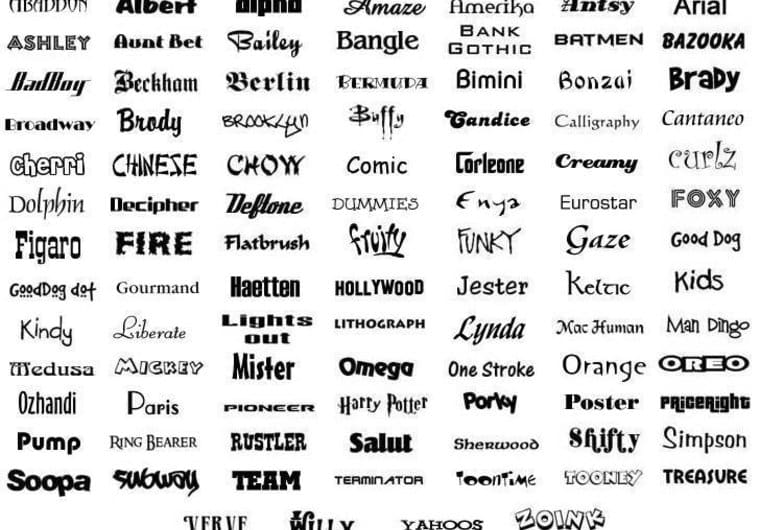
- Dotage
- Ecyr
- FixSys
- Lo-Res Nine Cyrillic
- Mobul
- Multicross
- AZ Poligon
- Strob
- Tablo
Шрифты табло
Акцидентные шрифты, имитирующие форму и фактуру знаков разнообразных шрифтов для информационных табло, матричных принтеров, жидкокристаллических дисплеев и других устройств, воспроизводящих шрифт с низким разрешением.
- Crystal
- Electronica
- Perfo
- Performance
Трафаретные
Акцидентные шрифты, имитирующие надписи, выполненные по трафарету. Знаки состоят из отдельных элементов, разделенных белыми перемычками. Иногда элементы знаков заполнены различными фактурами.
- Aksent
- Bardi
- Cliche
- Debby
- DJ Parade
- FavoritTraf
- Futura Eugenia
- Glasten
- Mania
- Nelma
- Plain
- Start
- Trafaret
- New Zelek
Натурные
Декорированные
Сюда относятся декоративные шрифты, предназначенные для акциденции, не укладывающиеся в предыдущие группы классификации, форма которых имеет преувеличенные детали или подверглась изменению с целью усиления декоративности.
Орнаментированные
- Orbi
Текстурированные
- Wind
Контурные, трехмерные, фактурные и выворотные
Акцидентные шрифты, знаки которых образованы контурами различной толщины, иногда с заполнением внутри, оттенением или и тем и другим. Иногда штрихи таких шрифтов заполнены фактурами или представляют собой негативное изображение.
- AdverGothic Cameo Bold
- Borjomi Decor
- Dotage
- Dynar Shadow
- EdgeLine Shadow
- Europe Shadow
- Futura Futuris Shadow
- Futura Futuris Volume
- Inform Shadow
- Izhitsa Shadow
- Josephine
- Leshy
- Sans Decor
- Tauern
- Template Gothic Cyrillic
Типы шрифтов, примеры и когда их использовать
Независимо от характера вашего дизайнерского проекта, различные типы шрифтов и окончательный выбор шрифта имеют решающее значение.
Шрифты помогают передать сообщение и передать чувство, связанное с сообщением. Выбор правильных шрифтов для ваших логотипов и других элементов дизайна может помочь в восприятии вашего сообщения или фирменного стиля.
какие существуют типы шрифтов?
Существует множество различных типов шрифтов, но в целом их можно разделить на следующие широкие категории:
- Шрифты с засечками: Эти шрифты имеют маленькие линии или «засечки» на концах толстых и тонких штрихов каждой буквы. Шрифты с засечками (например, New Roman) часто используются для печатных материалов, таких как книги и газеты, поскольку считается, что их легче читать в больших блоках текста.
- Шрифты без засечек: Шрифты без засечек не имеют засечек и имеют чистый современный вид. Они часто используются в качестве веб-шрифтов; в цифровых медиа, таких как веб-сайты и мобильные приложения, поскольку их легче читать на экранах.
- Шрифты Script: Шрифты Script имитируют рукописный почерк и имеют плавный элегантный вид.
Они часто используются для официальных приглашений и объявлений. - Дисплейные шрифты: Дисплейные шрифты предназначены для привлечения внимания и часто используются для заголовков и заголовков. Они бывают разных стилей, от смелых и массивных до изящных и богато украшенных.
- Моноширинные шрифты: Моноширинные шрифты имеют фиксированную ширину, что означает, что каждый символ занимает одинаковое количество места. Они часто используются для программирования кода и других технических приложений, где важно выравнивание.
- Рукописные шрифты: Рукописные шрифты имитируют рукописный текст и напоминают рукописную каллиграфию, чтобы добавить индивидуальности дизайну или логотипу бренда. Эти шрифты и каллиграфические шрифты часто используются для приглашений и других неформальных сообщений.
- Декоративные шрифты: Декоративные шрифты очень стилизованы и используются в особых случаях или для придания дизайну визуального интереса.
Декоративные шрифты бывают разных стилей, от богато украшенной каллиграфии до причудливых мультяшных шрифтов.
Как выбрать свой шрифт в мире с миллионами различных типов шрифтов
В наши дни у нас есть больше вариантов и различных переменных классификации шрифтов, чем когда-либо прежде.
Доступны тысячи шрифтов в различных стилях.
Однако навигация по различным шрифтам и выбор лучших шрифтов могут быть сложными.
В этом руководстве мы познакомим вас с основными типами шрифтов (от популярных шрифтов без засечек до декоративных), с тем, как они используются и как выбрать правильный шрифт, который передает нужную вам атмосферу.
Содержание
- Пять типов шрифтов
- Как выбрать шрифт?
Используйте красивые привлекательные шрифты в визуальных материалах и дизайне с помощью Piktochart. Попробуйте бесплатно.
Пять типов шрифтов
Несмотря на множество вариантов шрифтов, здесь мы перечисляем пять основных типов шрифтов, указатели, когда их использовать, и несколько примеров.
1. Шрифты с засечками
Примеры шрифтов без засечек : Georgia, Times New Roman, Beirut, Mermaid, Bodoni, Roslindale
Источник изображения: Donauhof WienШрифты с засечками относятся к числу оригинальных классических гарнитур, обычно используемых для профессионального и сложного дизайна.
Засечки включают небольшие выступы, завершающие штрихи их форм букв (называемые засечками, откуда этот стиль и получил свое название). Появившись в 1500-х годах, первые засечки были засечками в старом стиле. Этот стиль включает Garamond и Goudy Old Style. Преемники засечек старого стиля назывались переходными засечками, которые впервые появились в 1700-х годах. Эти шрифты имели высокий контраст штрихов и были более вертикальными, чем их предшественники в старом стиле.
Вы можете отличить шрифт с засечками от других по крошечным черточкам в верхнем и нижнем штрихах каждой буквы.
Что делает шрифты с засечками уникальными?
Шрифты с засечками уникальны, поскольку они имеют небольшие линии или завитушки, известные как «засечки», на концах штрихов, составляющих каждую букву.
Эти засечки придают шрифту более традиционный классический вид, который часто ассоциируется с печатными изданиями, такими как книги, газеты и журналы. Шрифты с засечками предназначены для удобного чтения в больших блоках текста, что делает их популярным выбором для объемного контента, такого как романы или академические статьи. Эксперты-типографы утверждают, что это самые разборчивые и легко читаемые шрифты без засечек.
Засечки в шрифтах с засечками помогают направлять взгляд читателя вдоль строки текста, облегчая его отслеживание и снижая нагрузку на глаза. Это связано с тем, что засечки создают «базовую линию» для каждой строки текста, что помогает глазу быстро и легко выровнять текст. Шрифты с засечками часто описываются как имеющие более формальный или традиционный вид и обычно используются в контекстах, где дизайнер хочет передать ощущение элегантности, изысканности или авторитетности.
Источник изображения: Галерея Drella В результате они являются первыми шрифтами, которые приходят на ум для различных проектов, таких как логотипы, печатные копии и веб-сайты.
И они придают вашему дизайну старомодный элегантный оттенок.
Шрифт с засечками считается заслуживающим доверия, консервативным и безопасным выбором практически в любом контексте, например:
- Заголовки и подзаголовки
- Основной текст, будь то короткие или длинные страницы текста
- Большие или маленькие размеры
Однако, как правило, их не рекомендуется использовать, если вам нужны крошечные размеры шрифта. Если вы разрабатываете что-то в основном для цифровых экранов, вы можете рассмотреть другие типы шрифтов, которые мы обсудим ниже.
2. Шрифты без засечек
Примеры: League Spartan, Fredoka One, Aileron, Bebas Neue, Zelda
Источник изображения: Blog With Joy по умолчанию на цифровых устройствах.Вы можете найти их почти в каждой книге, документе или другой публикации.
Шрифт без засечек относится к шрифтам без штрихов, уникальным для шрифтов с засечками.
В чем разница между шрифтами с засечками и шрифтами без засечек?
Основное различие между шрифтами с засечками и шрифтами без засечек заключается в том, что шрифты с засечками имеют тонкие штрихи/небольшие линии или завитки на концах штрихов, составляющих каждую букву (известные как «засечки»), в то время как шрифты без засечек имеют нет.
Шрифты с засечками часто ассоциируются с печатными материалами, такими как книги, образовательные ресурсы, газеты и журналы, и предназначены для удобного чтения больших блоков текста. Засечки в шрифтах с засечками помогают направлять взгляд читателя вдоль строки текста, облегчая его отслеживание и снижая нагрузку на глаза. Шрифты с засечками часто описываются как имеющие более традиционный или классический вид и обычно используются в контекстах, где дизайнер хочет передать ощущение элегантности, изысканности или авторитетности.
С другой стороны, шрифты без засечек часто ассоциируются с цифровыми медиа, такими как веб-сайты, мобильные приложения и платформы социальных сетей. Они имеют чистый современный вид и часто используются для коротких фрагментов текста, таких как заголовки или подписи. Шрифты без засечек предназначены для удобного чтения на экранах, которые, как правило, имеют более низкое разрешение, чем печатные носители. Их часто описывают как более непринужденные или неформальные, с неоклассическим дизайном.
Они обычно используются, когда дизайнер хочет передать ощущение современности, простоты или дружелюбия.
В целом, выбор между шрифтами с засечками и без засечек зависит от конкретного контекста и целей дизайна. Шрифты с засечками часто используются для формального или традиционного контекста, а шрифты без засечек часто используются для неформального или современного контекста.
На протяжении всей истории они не были так популярны, как засечки, но стали заметны с появлением компьютеров и других цифровых устройств.
Это было примерно тогда, когда немецкие дизайнеры экспериментировали с формами букв без ножек и разработали культовые шрифты, которые чрезвычайно популярны сегодня, такие как Helvetica и Futura.
Шрифты без засечек также можно разделить на несколько подкатегорий, включая гротескные, квадратные, геометрические и гуманистические стили. Бренды, которые используют шрифты без засечек в своих логотипах: LinkedIn, Calvin Klein и The Guardian.
Разборчивый и жирный шрифт без засечек теперь является синонимом простоты, эффективности и современного внешнего вида.
Они также считаются самыми экономичными и чистыми шрифтами.
Из-за отсутствия мелких штрихов в буквах шрифты без засечек менее детализированы и более разборчивы в определенных контекстах.
Например, они хорошо адаптируются даже в небольших размерах или на цифровых экранах.
Они легко читаются независимо от размера шрифта или длины текста.
Это делает шрифт без засечек мастером на все руки.
Кроме того, шрифт без засечек считается жирным и более творческим шрифтом, чем традиционный и консервативный шрифт с засечками.
По этой причине они чаще используются в логотипах и заголовках, чем в длинных абзацах.
Выберите шрифт без засечек, если вам нужен минималистичный или современный вид.
3.
Шрифты ScriptПримеры шрифтов Script : Alex Brush, Broadley, Pacifico, Barista, Great Vibes
Источник изображения: Begindot Шрифты Script идентифицируются курсивом, рукописным или каллиграфическим стилем буквы.
Их формы букв и стили шрифта больше всего похожи на рукописный почерк.
Благодаря этому они сочетают изящность стилей шрифтов с засечками с более красивым и аутентичным дизайном.
Источник изображения: BegindotТип шрифта script лучше всего использовать для романтических обложек книг и свадебных приглашений или правильный шрифт, когда вы хотите, чтобы ваши дизайны выглядели более историческими.
И они исключительно хорошо работают в логотипах, заголовках и цитатах.
Сила этого типа шрифта заключается в его уникальности и смелости, но за счет удобочитаемости. Поэтому очень важно использовать его экономно.
Шрифты Script обычно не используются для длинных текстов или отрывков.
4.
Экранные шрифтыПримеры этого семейства шрифтов: Gilroy, Athetik, Made Canvas, Margaret, Playfair
Источник изображения: Neuron Themes Экранные шрифты (также известные как декоративные) самые сложные шрифты идентифицировать, поскольку они не следуют каким-либо общим правилам.
Эти шрифты являются одними из самых уникальных и охватывают множество стилей, таких как граффити, абстрактные и трехмерные формы.
Источник изображения: Neuron Themes5.
Шрифты Slab SerifПримеры : Typnic, Comply, Artegra, Bebop, Fanatix
Источник изображения: Design InspirationШрифты Slab serif самые заметные и самые громкие засечки. Думайте об этих шрифтах с засечками как о более энергичном и восторженном брате спокойных и классических шрифтов без засечек.
Шрифты с засечками возникли в начале 19 века, когда была разработана новая технология печати, называемая «плоскими» или «египетскими» шрифтами. Эти шрифты были разработаны, чтобы быть смелыми и привлекающими внимание, с толстыми прямоугольными засечками, которые создавали характерный «блочный» вид.
Первые шрифты с засечками были разработаны Винсентом Фиггинсом, известным типографом и шрифтовиком из Лондона, в начале 1800-х годов.
Фиггинс создал шрифт Antique с толстыми, похожими на плиты засечками и жирными штрихами. Шрифт имел мгновенный успех и быстро стал популярным в рекламе и дизайне плакатов.
В США первые шрифты с засечками были разработаны компанией American Type Founders в середине 19 века. Эти шрифты были основаны на более ранних британских образцах, но были адаптированы для американского рынка и стали особенно популярными в газетных заголовках и рекламе.
Они предназначены для чтения с большого расстояния и активно используются на рекламных щитах, брошюрах и плакатах в течение нескольких десятилетий.
Источник изображения: Design InspirationВ последнее время они также превратились в формы, которые можно использовать для длинных абзацев текста. Шрифт Clarendon – хороший пример.
В целом шрифты с засечками передают винтажную художественную атмосферу и неоспоримый суровый атлетизм. Они отлично подходят для брендов товаров для активного отдыха.
Как выбрать шрифт?
Мы рассмотрели несколько идеальных сценариев использования основных типов шрифтов.
Но есть некоторые дополнительные факторы, которые необходимо учитывать при выборе палитры шрифтов для вашего дизайн-проекта. Итак, давайте посмотрим на них.
1. Индивидуальность вашего бренда
Выбранные вами шрифты должны соответствовать визуальным атрибутам вашего бренда и его нише. Например, типографика косметического бренда будет отличаться от ИТ-бренда.
Отличный способ понять это — изучить шрифты, используемые брендами, похожими на ваш. Вам не нужно красть одни и те же шрифты, но вы получите общее представление о том, на что стрелять.
По словам Скотта Чоу из Blog Starter, индустрия моды является ярким примером этой тенденции, где более 70% модных брендов используют шрифты Geometric San Serif.
Также подумайте, какие цвета вы собираетесь использовать. Вы бы хотели использовать светлые цвета с экстравагантными шрифтами и насыщенные цвета с неброскими шрифтами.
Если, например, и цвета, и шрифты кричащие, то ваш дизайн будет больше похож на цирковую афишу.
2. Количество используемых шрифтов
Выберите один шрифт в качестве основного. Это будет использоваться чаще всего, особенно в больших размерах, таких как заголовки. Вы можете стать смелым и уникальным при выборе основного шрифта, потому что он нужен не только для удобочитаемости, но и для создания настроения.
После этого выберите другой шрифт в качестве вторичного. Это будет использоваться для основного текста и других больших абзацев. Поскольку удобочитаемость имеет важное значение, вы должны в первую очередь обращать внимание на то, чтобы шрифт был простым и легко читаемым.
При необходимости вы также можете выбрать третий шрифт. Вы можете использовать его экономно для таких элементов, как призыв к действию, кнопки, меню и т. д. Он может быть немного причудливым, как основной шрифт, но он не должен затмевать другие ваши шрифты.
Всегда помните об иерархии шрифтов при их использовании в проекте. Ваши основной, дополнительный и другие шрифты имеют разный вес и должны использоваться как таковые.
Бывают случаи, когда оправдано использование более трех шрифтов, но золотое правило в большинстве случаев — придерживаться только двух или трех.
3.
Контраст между шрифтамиСледующим важным аспектом является правило контрастов. Это вступает в игру, когда вы сочетаете два или более шрифта в качестве заголовка + подзаголовка или заголовка + основного текста.
Использование двух одинаковых шрифтов — прямой путь к катастрофе. Ваш дизайн будет выглядеть запутанным и непрофессиональным. Всегда выбирайте шрифты, которые кажутся очень разными при объединении.
Например, вы можете сопоставить рукописный шрифт в заголовке со шрифтом с засечками в основном тексте. Или соедините шрифты без засечек (например, Brandon Grotesque) с засечками (например, Baskerville).
Пример сочетания шрифтов с хорошей контрастностью Комбинируемые шрифты не обязательно должны принадлежать к разным семействам шрифтов, если они имеют достаточную контрастность.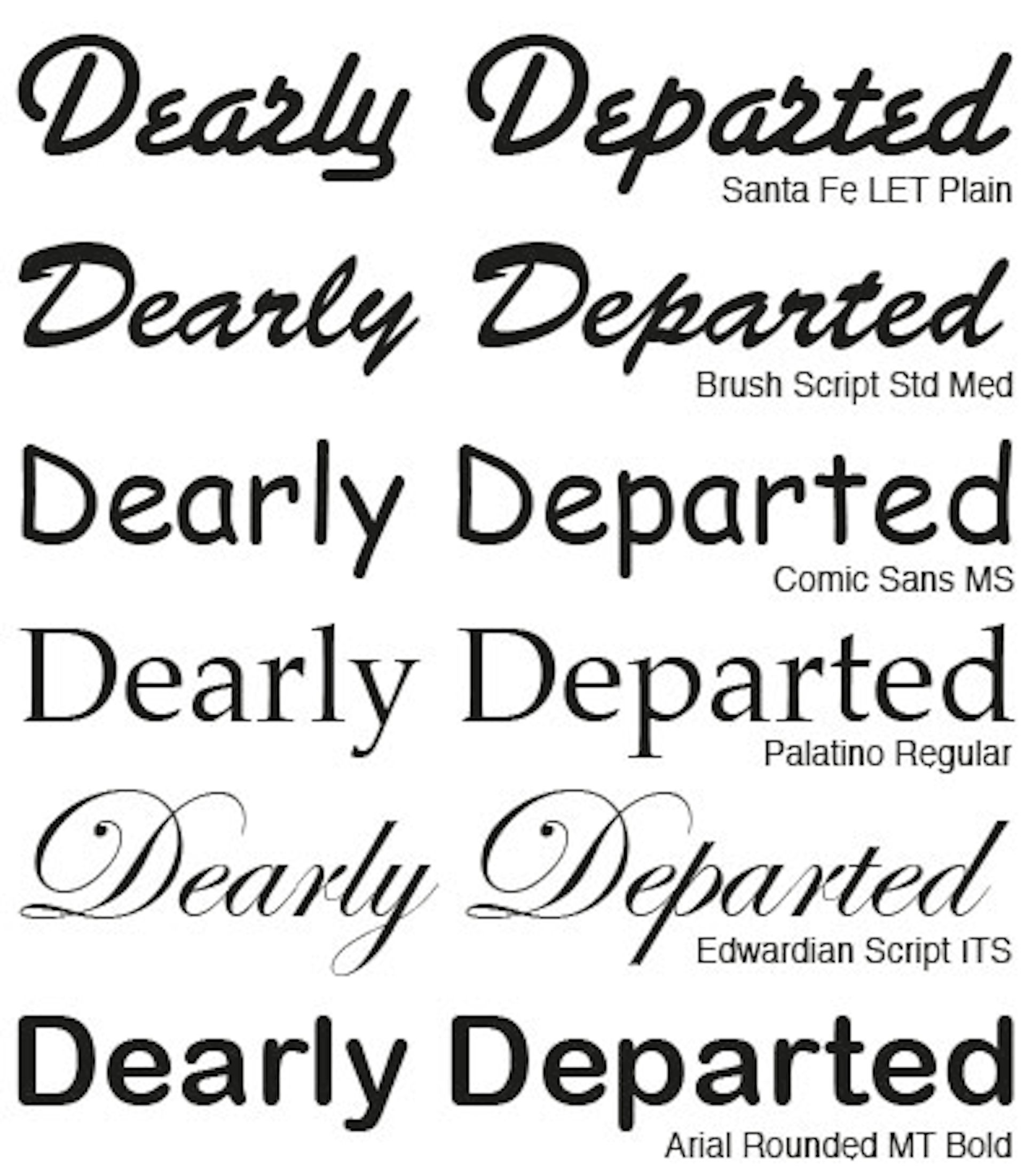
Например, большинство шрифтов без засечек имеют разные интервалы между буквами и вариации веса, которые можно использовать по-разному в одном проекте.
Вы можете использовать сжатую, полужирную версию в заголовке и обычную, облегченную версию в длинных текстах.
4. Разборчивость экрана и страницы
Наконец, выбор шрифта должен учитывать удобочитаемость вашего сообщения на различных экранах, размерах и форматах страниц.
Игнорирование этого аспекта может привести к тому, что дизайн будет трудночитаемым и создаст ненужную нагрузку на глаза.
Подумайте, предназначен ли ваш дизайн для цифровых экранов, печати или для того и другого. И убедитесь, что ваш выбор шрифта отражает это.
Ваш следующий шаг: поэкспериментируйте со шрифтами
Имея в своем распоряжении различные типы шрифтов и лучшие практики, пришло время выбрать шрифты для вашего дизайнерского проекта.
Руководящие принципы бренда, безусловно, облегчают работу, но опыт и эксперименты не сравнимы ни с чем.
Иногда то, что вы думали, будет работать, может оказаться неправильным, а в других случаях сочетание, в котором вы меньше всего доверяли, может работать как шарм.
Все это часть процесса. Даже самые опытные дизайнеры пробуют разные комбинации шрифтов, чтобы найти то, что им нужно.
Чем больше вы работаете с разными шрифтами, тем лучше вы будете использовать их для достижения желаемого результата. Так что рискуйте и получайте удовольствие!
64 классных шрифта, которые вы захотите использовать в 2023 году
Дизайнер из ThoughtWorks однажды сказал: «Когда типографика на высоте, слова становятся изображениями». И действительно, Шон Лукас был прав.
Графический дизайн — это то, что привлекает внимание, как и классные шрифты. При правильном выборе, будь то пользовательский или бесплатный шрифт, выбор шрифта передаст правильное сообщение. Когда кто-то демонстрирует шрифты и звездный графический дизайн, ожидайте, что он привлечет больше сторонников бренда.
Почему?
Согласно Engadget, вот восемь причин, по которым шрифт или типографика в целом являются краеугольным камнем в маркетинге.
- Общается с вашей аудиторией
- Привлекает ваших читателей
- Удерживает внимание аудитории
- Вызывает определенные настроения и чувства
- Устанавливает структуру
- Создает гармонию дизайна
- Излучает профессионализм
- Утверждает авторитет
Используйте только лучшее шрифты для вашего бренда. Взаимодействуйте со своей аудиторией, передавая свое сообщение с помощью шрифтов. Penji может помочь вам в этом. Используя Penji, вы получите убедительные и высококачественные изображения. Кроме того, запрашивайте любые дизайны, которые вам нужны, по бюджетной ежемесячной ставке! Узнайте больше о том, как работает платформа Penji.
Поэтому, когда вы думаете об эксклюзивных шрифтах, чтобы сделать ваши дизайны или логотипы выделяющимися, убедитесь, что они соответствуют вашей личности и имиджу.
Давайте перейдем к делу и покажем вам 64 классных шрифта, которые повышают узнаваемость бренда.
Крутые шрифты SERIF
1. Fakedes Кирилла Михайлова Из-за своей чистой, округлой формы и двойных линий Fakedes — классный шрифт, который отлично подходит для заголовков.
Этот удивительный шрифт, Forum, напоминает старое римское писание времен Римской империи с современным оттенком.
Вам также могут понравиться: Шрифты для дизайнеров, которые вы тоже могли бы использовать
3. Muchacho от Джеффа Шрайбера Этот классный шрифт источает ретро-стиль. Поскольку это шрифт с заглавными буквами, этот стиль идеально подходит для заголовков или заголовков.
Если вы хотите привнести в свой дизайн немного Дикого Дикого Запада, вестерн Barbaro сочетает в себе современность и галантность.
Это уникальный и особенный шрифт, излучающий стиль и класс. Я почти могу видеть это на витринах модных бутиков, продающих платья от кутюр высокого класса.
6. Lovato Light от PhilatypeЭффективно создавайте умные и эффективные кампании
Достигайте целей конверсии с помощью выделяющихся визуальных эффектов
Мне это нужно!
Для более изящного и простого шрифта с засечками идеально подойдет Lovato Light. Это свежо и создает незагроможденную привлекательность.
Крутые шрифты — это изюминка, которая делает ваши проекты яркими. Одним из примеров является игривый шрифт с засечками Valkyrie.
Вам также может понравиться: 25 лучших шрифтов для Интернета (ссылки для загрузки внутри)
8.
Palacio Натана Томсона Кто сказал, что традиционное и современное несовместимы? Шрифт Palacio достаточно крут для вашего современного дизайна, но он урезан до красивого традиционного вида.
Еще один потрясающий шрифт в стиле Old Western — Blnc. Он подходит практически для любых печатных или цифровых материалов.
Округлая эстетика шрифта Modum создает дружелюбную и современную атмосферу, делая его красивым и изысканным.
Вам также может понравиться: Лучшие шрифты для логотипов, которые не сделают ваш бренд дешевым
11. Matchbook by Simon Walker Этот превосходный шрифт кричит о западном и мужественном стиле и подходит для заголовков вашего проекта. Стиль с засечками немного расширен, что делает шрифт еще более заметным.
Что делает Kawoszeh потрясающим шрифтом для любого дизайна, так это его тонкие и деликатные штрихи, которые не похожи ни на что другое.
Ничто не сравнится с уникальностью шрифта Bobber для ваших дизайнерских заголовков. Это все заглавные и похожие на плиты.
Вам также может понравиться: Бесплатные шрифты для коммерческого использования (быстрая загрузка)
14. Dude by Dan Gneiding Если вы думаете, что ковбои — это круто, то этот стиль шрифта подойдет для всего вашего веселья и творчества дизайн с намеком на старую западную атмосферу.
Шрифт Choplin прост и нейтрален. Чоплин, выделенный жирным шрифтом, также подходит для плакатов или любых маркетинговых печатных изданий. Это даже читаемый шрифт для Интернета.
Этот стильный и девчачий шрифт без засечек отлично сочетается с женственными дизайнерскими проектами.
Вам также могут понравиться: 64 крутых шрифта, которые вы хотите использовать
17. Stig by Alex Hedin Стиг напоминает мне мощный автомобиль, мощность которого не уступает Ferrari. Он чистый, классический, но динамичный.
Акцентированный геометрическими фигурами шрифт Колико содержит буквы славянских языков.
Этот художественный шрифт состоит из геометрии и линий. Когда оба сплетены вместе, в результате получается этот уникальный шрифт, идеально подходящий для нео-классического дизайна.
Вам также могут понравиться: Шрифты 101: Полезное руководство по брендингу вашего бизнеса
20. Certa Sans by Glen 9 января0015 Простая, но компетентная, Certa Sans воплотит в жизнь любой ваш дизайн. Он также добавляет современный штрих к любой типографике или графике в целом.
Некоторые буквы в этом шрифте кажутся наклонными, что выделяет шрифт Ralev без засечек.
Dozer — крупный шрифт, который отлично подходит для дополнительных материалов с крупным шрифтом. Тем не менее, вес никоим образом не доминирует над стилем.
Еще один шрифт с заглавными буквами, Baron излучает современный стиль, смешанный с чертой классической привлекательности. Наконец, творческие бары завершают его уникальным образом.
Для дизайна, который находит отклик у веселой и непринужденной аудитории, Rhyder является подходящим шрифтом. Он непринужденный, но с профессиональным тоном.
Вам также может понравиться: БЕСПЛАТНЫЕ классные шрифты для логотипов, которые нужны каждому дизайнеру
25.
Fins by Jake Kho Этот шрифт с закругленными и заостренными краями напоминает вам об океанских стихиях. И да, он вдохновлен рыбой в океане!
Для мягких и деликатных курсивных штрихов Alex Brush может справиться с этой задачей. Он может представлять любую компанию с более формальным брендингом.
Что делает шрифт Lobster Two классным, так это то, что он достаточно универсален для использования в любом типе графического дизайна.
Я вижу Arizonia на свадебных приглашениях или логотипе ювелирного магазина. Этот шрифт классный и стильный.
Вам также может понравиться: Руководство по бизнес-шрифтам: как выбрать лучший шрифт и шрифты для вашего бизнеса0002 Нежные штрихи и легкий вес мандарина создают роскошную привлекательность, подходящую для известных и традиционных брендов.
Этот рукописный шрифт не устрашающий и не жесткий. Напротив, это весело и профессионально одновременно.
Этот шрифт заслуживает того, чтобы быть в этом списке «крутых шрифтов» из-за его изящных курсивных штрихов.
Burlington Script — это полужирный шрифт с гладкими и четкими изгибами, похожими на маркер.
Если вам нужен более смелый шрифт, не теряя декоративных штрихов, QumpellkaNo12 — подходящий выбор.
Самая поразительная особенность Kingthings — линии, похожие на граффити, которые делают его уникальным среди других рукописных шрифтов.
Смелость Condiment не умаляет сдержанной привлекательности рукописных шрифтов.
Trashco имеет старомодный западный вид, что делает его сурово привлекательным.
Я почти мог видеть, как буквы движутся под фоновую музыку мультфильма или кулинарного шоу. Меловой стиль идеально подходит для забавных дизайнерских проектов.
Sniper имеет размытый вид, что делает его свежим и необычным.
Pentagon выполнен в ретро-западном стиле. Однако звезды, разбросанные по каждой букве, добавляют современности.
Этот шрифт может сойти за приглашения и плакаты на Хэллоуин или готические вечеринки из-за его жуткого вида.
Хотя KR Keltic One следует использовать с осторожностью, этот стиль выделяется своим кельтским искусством.
Этот декоративный шрифт имеет смелый вид, но маленькие сердечки смягчают величественное самообладание.
Красивые завитушки этого, казалось бы, рукописного письма выделяют этот шрифт.
Созданный на основе шрифта Addam’s Family, шрифт Fiddums Family жуткий, меланхоличный и завораживающий одновременно.
Мы не можем закончить этот список «крутых шрифтов», не включив слишком мягкий стиль. Смелость и женственность этого шрифта актуальны для дизайна с женской аудиторией.
Крутые СРЕДНЕВЕКОВЫЕ шрифты 46. Королевский шрифт от Aldus Этот средневековый шрифт кричит о королевской власти. Это один из тех причудливых старых английских шрифтов, которые можно использовать для приглашений или даже татуировок.
По словам пользователей, шрифт работает только в том случае, если вы нажмете клавишу Caps Lock на клавиатуре.
Черная магия опирается на более мрачное представление о средневековье. Это классный шрифт для фэнтезийных или исторических дизайнов.
48. Шрифт Anchor Steam NF от Nick’s FontШрифт Anchor steam представляет собой превосходную смесь ар-деко и некоторых средневековых элементов. Стилизованные прописные буквы «А» и «У» выглядят со вкусом.
49. Шрифт Sable от Кевина РичиSable — средневековый шрифт, похожий на каллиграфию с ломаными линиями. Несмотря на то, что это кажется фантастическим, шрифт должен использовать его экономно, поскольку дизайн верхнего регистра сложно различить.
50. Шрифт PentaGram Salemica от FULL MOON Design House Оккультные и магические темы вдохновили дизайн этого шрифта Salemica.
Стилизованная буква «А» выглядит интересно, так как выглядит как наконечник стрелки или незавершенный треугольник.
Шрифт Coffee Tin имеет двухцветный шрифт. Это классный старинный шрифт, который идеально подходит для этикеток, вывесок и плакатов.
52. Шрифт Deadhand Карта сокровищ от GemfontsЭтот сказочный старинный шрифт выглядит как рукописный. Некоторые пользователи включили этот шрифт в свой тематический день рождения, приглашение и дизайн игры.
53. Шрифт Faulmann от DaredemotypoЭтот старинный шрифт вдохновлен глифами. Дизайнер шрифта взял за основу книгу Карла Фаулмана «Das Buch der Schrift».
54. Шрифт Coventry Garden от Nick’s FontДизайн фирменных бланков старых книг вдохновил Coventry Garden на стильное обращение с прописными буквами.
Крутые 3D-шрифты 55.
Шрифт Xtrude от Garphynk Этот фантастический 3D-фасад имеет драматический эффект выдавливания. В целом эффект выглядит так, будто на шрифт отбрасывается тень.
56. Шрифт Adamas от ColorblindЭтот шрифт имеет превосходный геометрический эффект, который выглядит как каркас. Это забавный шрифт для футуристического дизайна.
57. Шрифт Neon Lights от Allen R. WaldenШрифт Neon Lights — еще один классный 3D-шрифт, идеально подходящий для футуристического дизайна. Эффект шрифта выглядит металлическим и несколько блестящим.
58. Шрифт BLOCKHEAD от RebeccaBlockhead — забавный трехмерный шрифт, который выглядит как нарисованный от руки. Это лучше всего подходит для причудливых дизайнерских выходов.
59. Шрифт «Тень для вечеринки в среду» от Brand Labs Шрифт «Тень для вечеринки в среду» вдохновлен старинными театральными буквами.
Дизайнер придает ему современный вид, добавляя драматический эффект тени.
Этот шрифт имеет забавный эффект трехмерных точек, благодаря которому буквы выглядят так, как будто они состоят из молекул.
61. Шрифт Demon Cubic Block от FODDemon Cubic Block выглядит как шрифт, вдохновленный игрой Tetris. Он имеет забавный 3D-эффект, когда кубические блоки складываются вместе, образуя букву.
Шрифт Cool HOLIDAY s 62. Sketch Bones Font by CharacterЭтот невероятный шрифт имеет функцию наброска, в которой кости образуют буквы. Он идеально подходит для Хэллоуина или дизайнерских проектов на тему ужасов.
63. Шрифт Candy Stripe от Aenigma FontsЭтот великолепный праздник имеет эффект полосок леденца. Это забавный шрифт для рождественских дизайн-проектов.
64. Шрифт Easter Bunny от Дитера Штеффмана Давайте завершим этот список причудливым и веселым праздничным шрифтом, который идеально подходит для пасхальных дизайнерских проектов.
Не соглашайтесь на дизайн, который утомит ваших покупателей или клиентов. Коснитесь Penji, чтобы узнать о своих потребностях в дизайне. Следуйте этим простым шагам, чтобы запросить дизайн на нашей платформе.
Шаг 1: Создайте проект и свяжитесь с дизайнеромПосле регистрации в Penji вы получите доступ к платформе Penji. Наконец-то вы можете запросить проект. Для этого нажмите на Новый проект .
Затем выберите тип дизайна, который вы запрашиваете. Не можете найти? Вместо этого создайте пользовательский проект .
После этого, пожалуйста, предоставьте подробное описание дизайна с классным шрифтом, который вы хотите использовать в своем дизайне. Таким образом, ваш дизайнер может начать работать над ним сразу после того, как вы нажмете «Отправить».
После этого мы назначим вам одного из наших профессиональных и заслуживающих доверия дизайнеров для работы над проектом.
Они представят первый дизайн в течение 24–48 часов.
Через 24–48 часов вы, наконец, получите первый черновик. Отсюда вы можете либо загрузить его уже, либо просмотреть его дальше, отредактировав его.
Используйте функцию «укажи и щелкни», встроенную в платформу Penji. Таким образом, вы можете указать области, которые нуждаются в улучшении. У вас не будет проблем с недопониманием с вашим дизайнером. Кроме того, используя это, ваш дизайнер может отправить исправленную версию в течение 24 часов.
Они часто используются для официальных приглашений и объявлений.
Декоративные шрифты бывают разных стилей, от богато украшенной каллиграфии до причудливых мультяшных шрифтов.